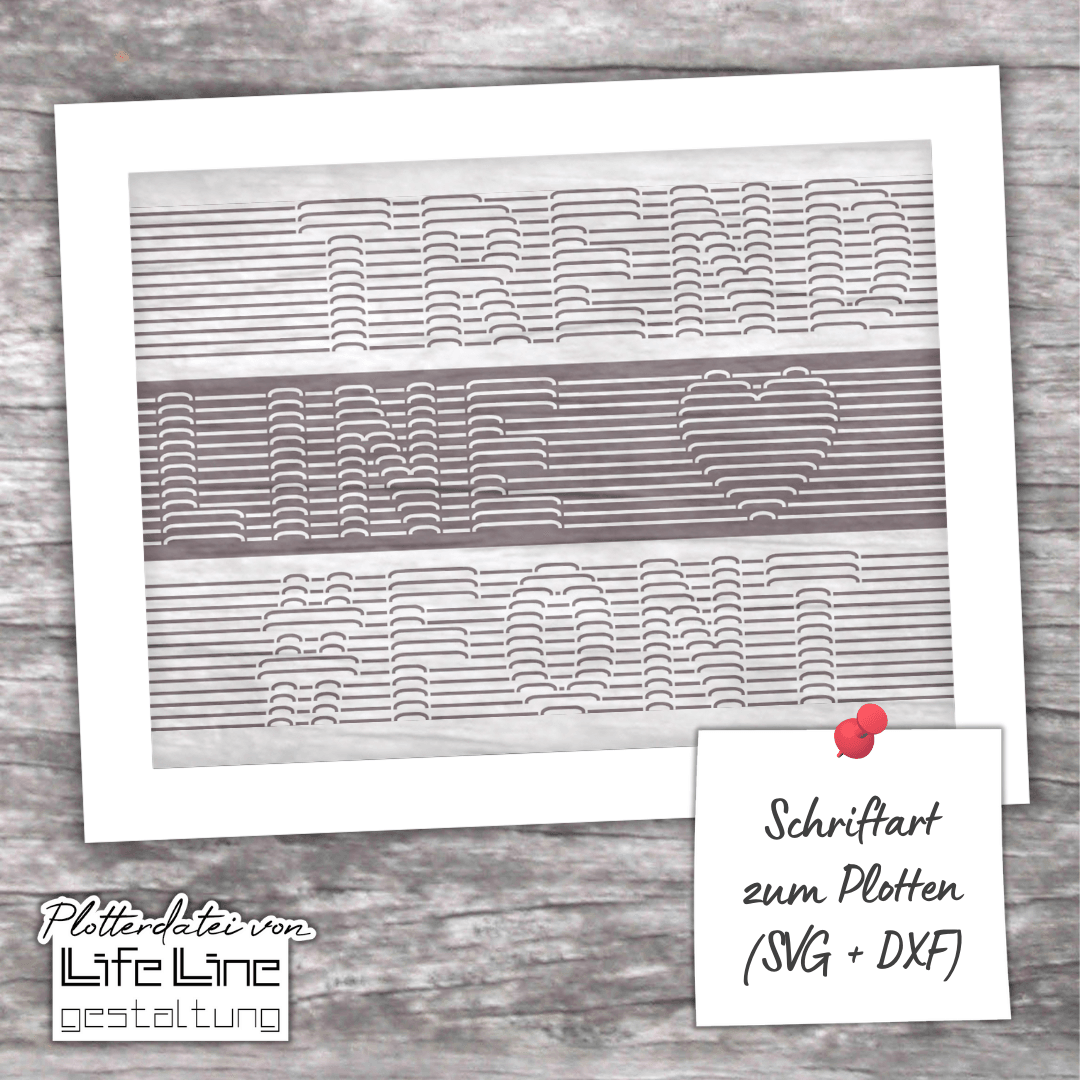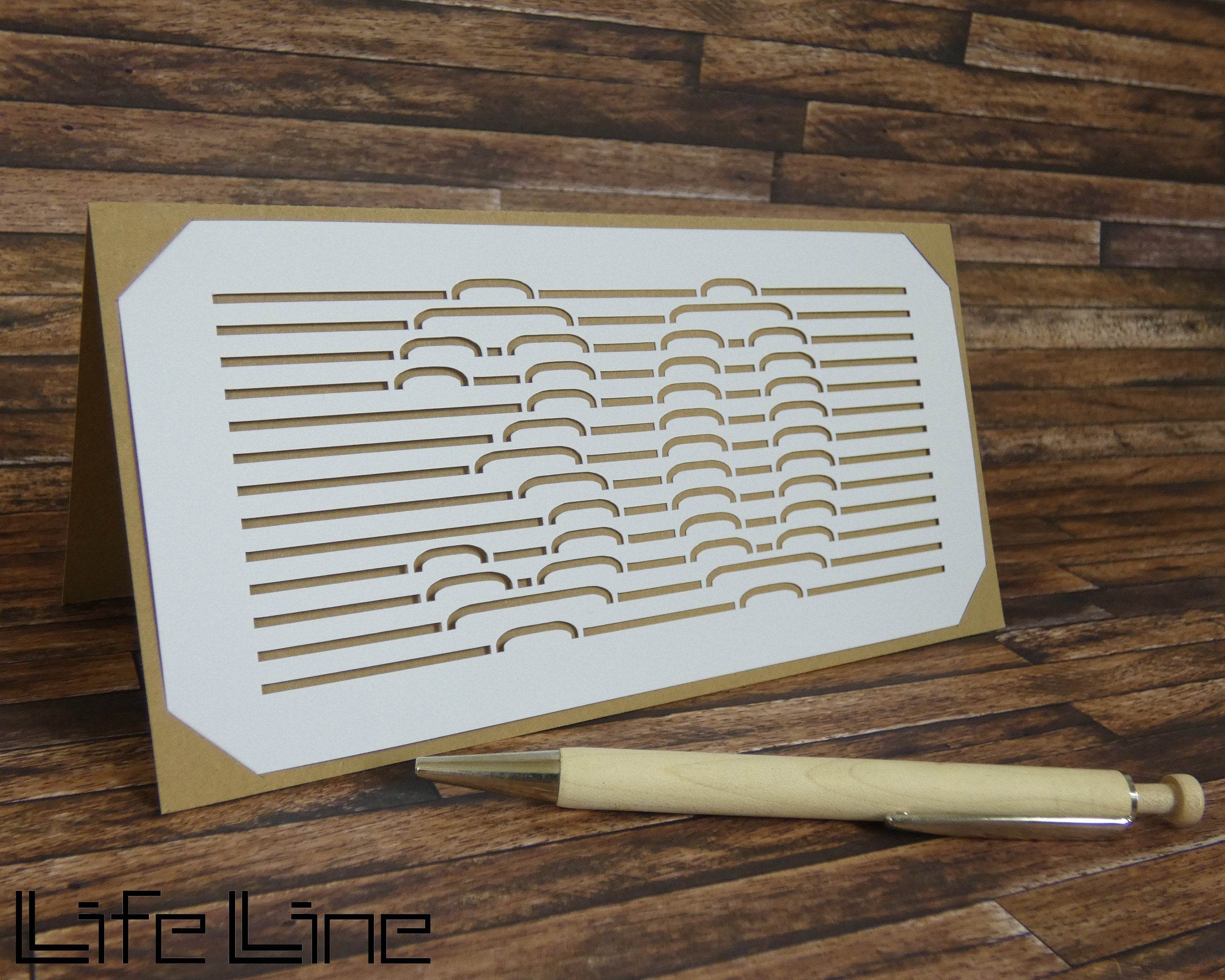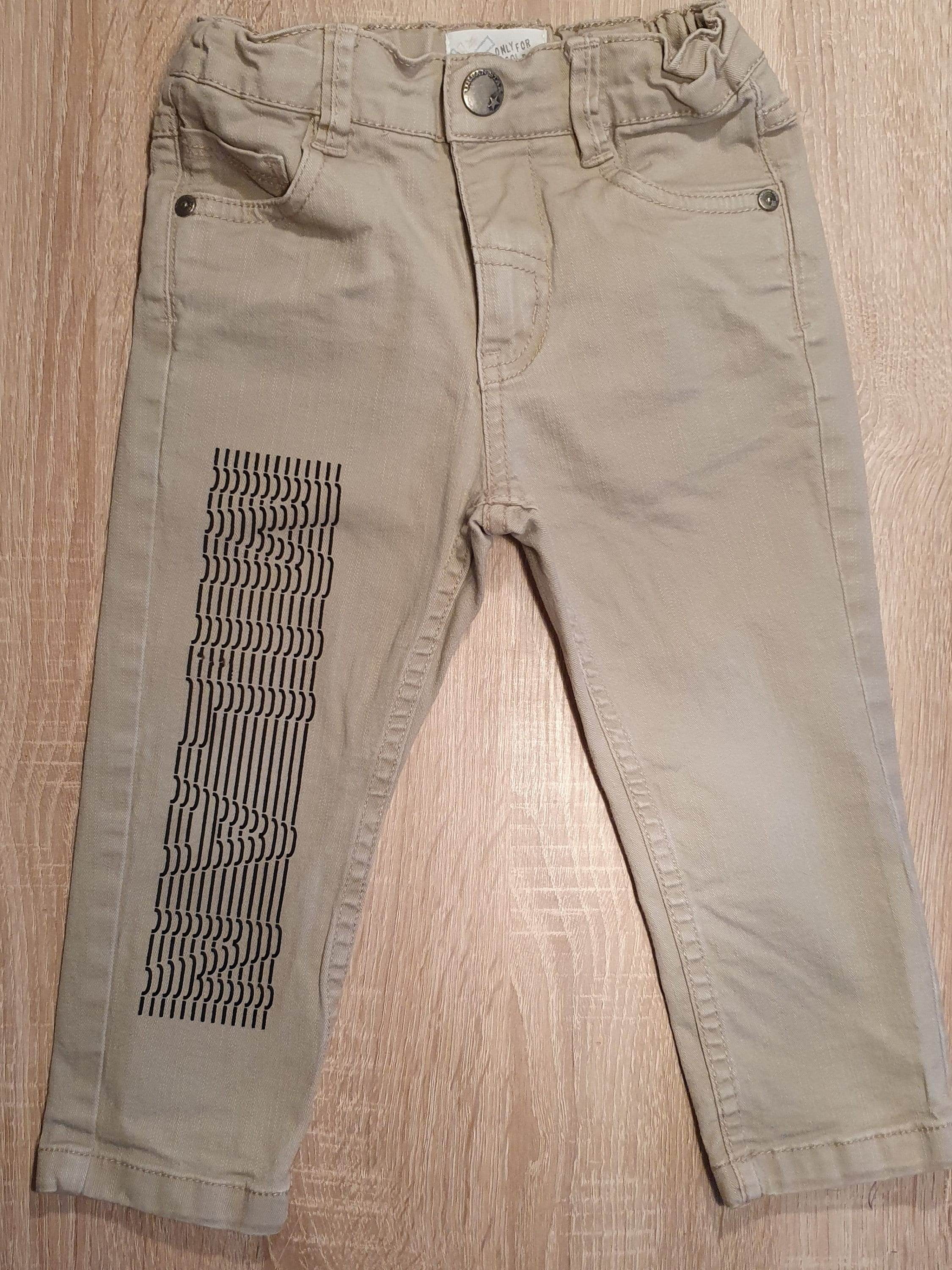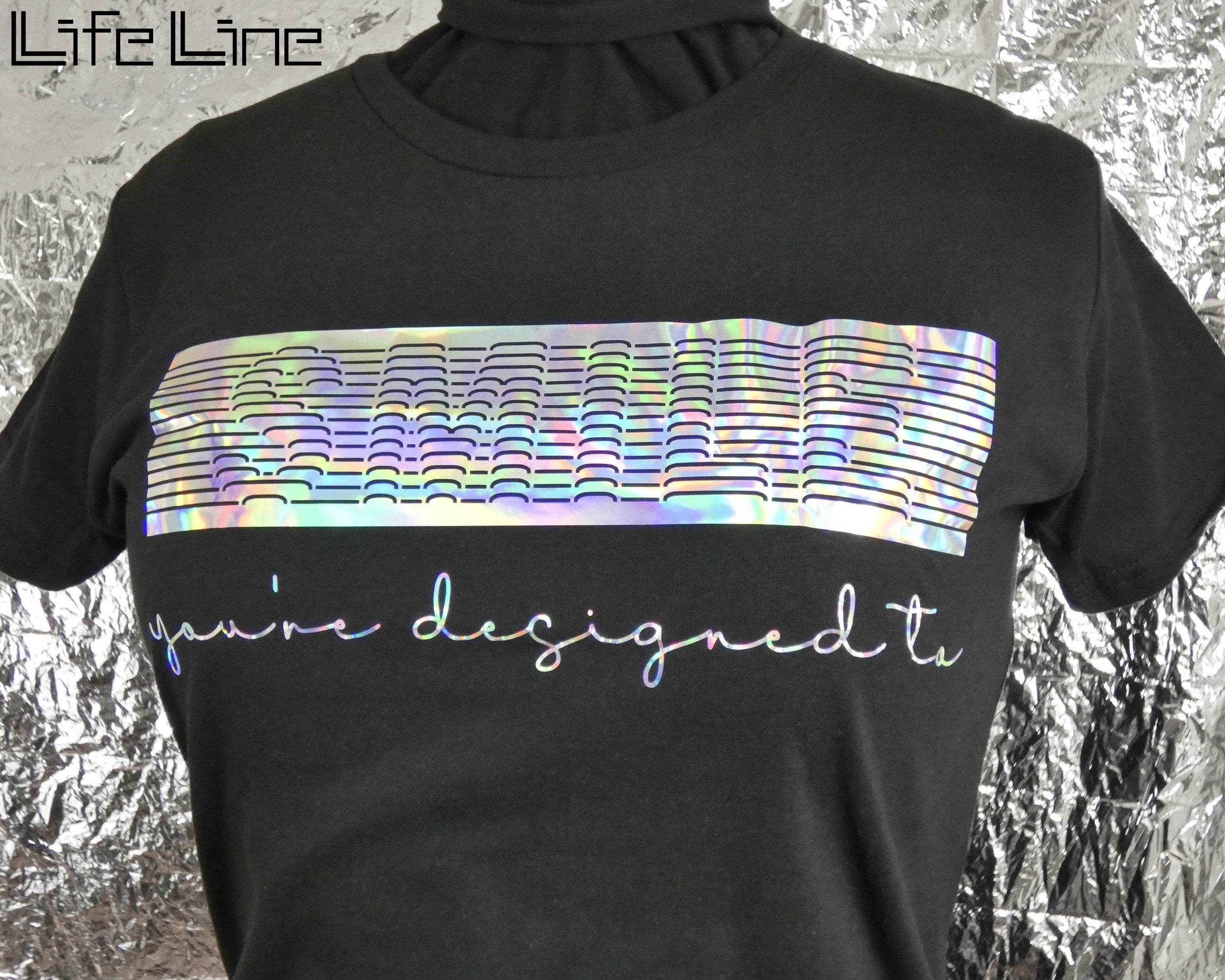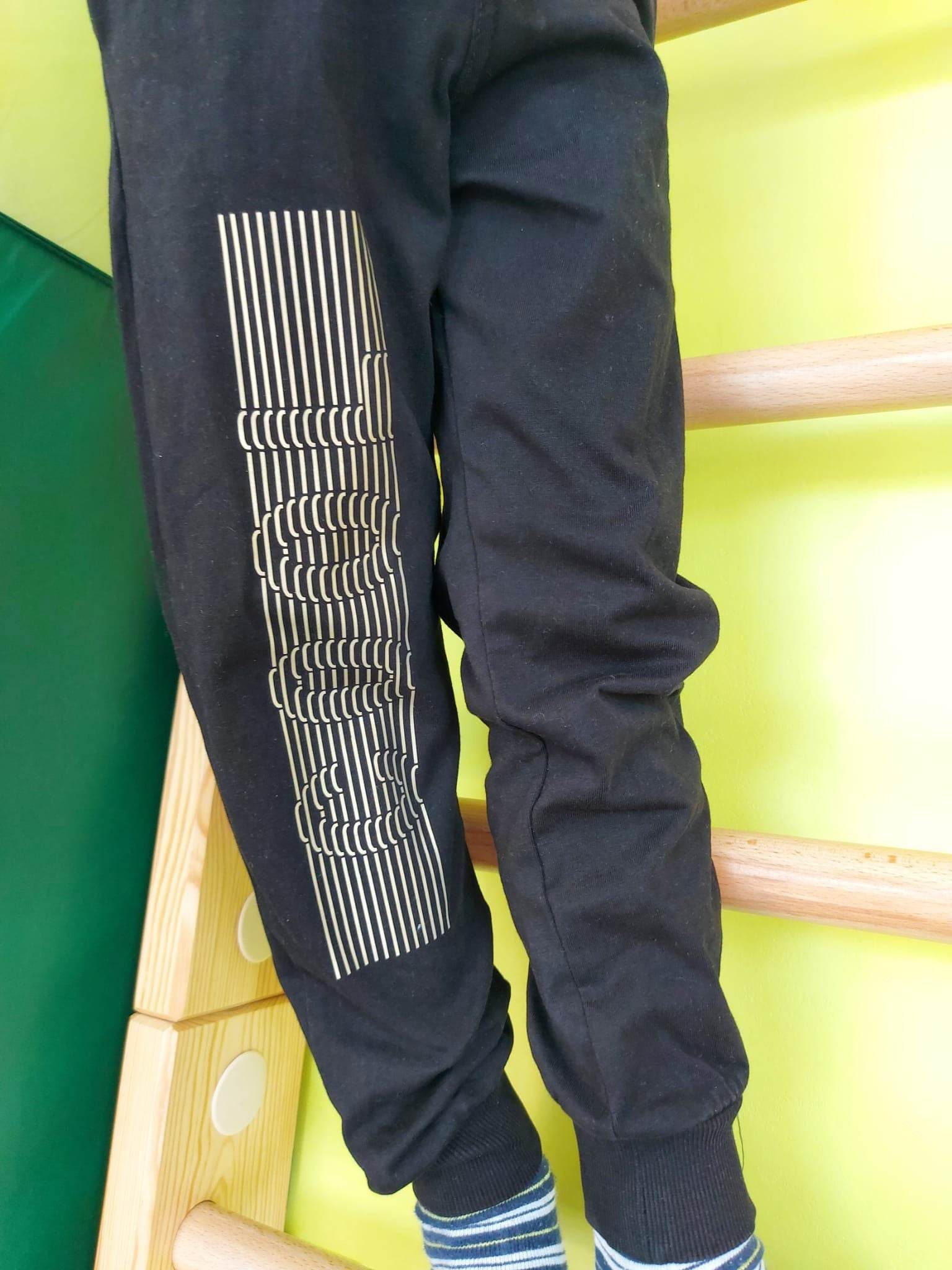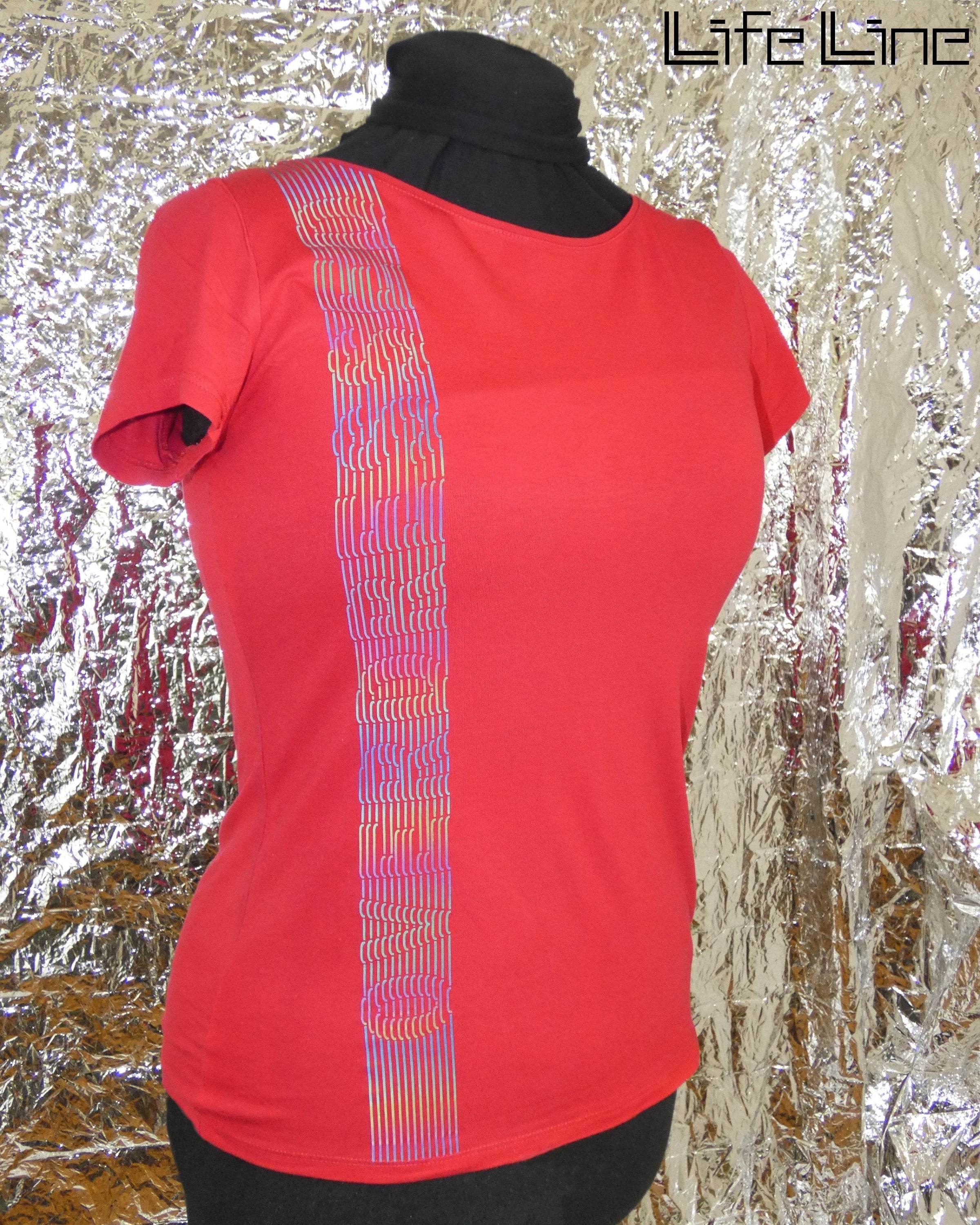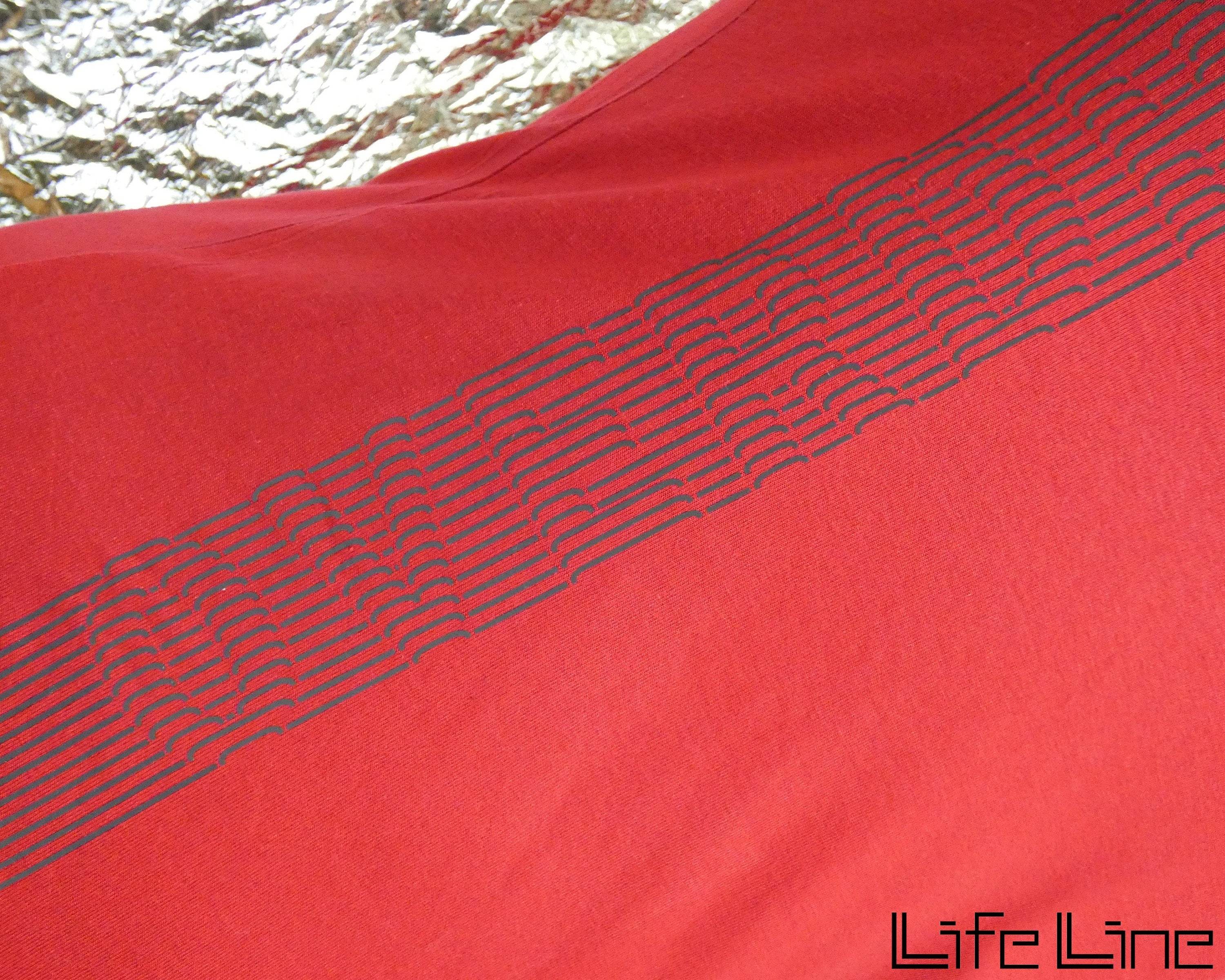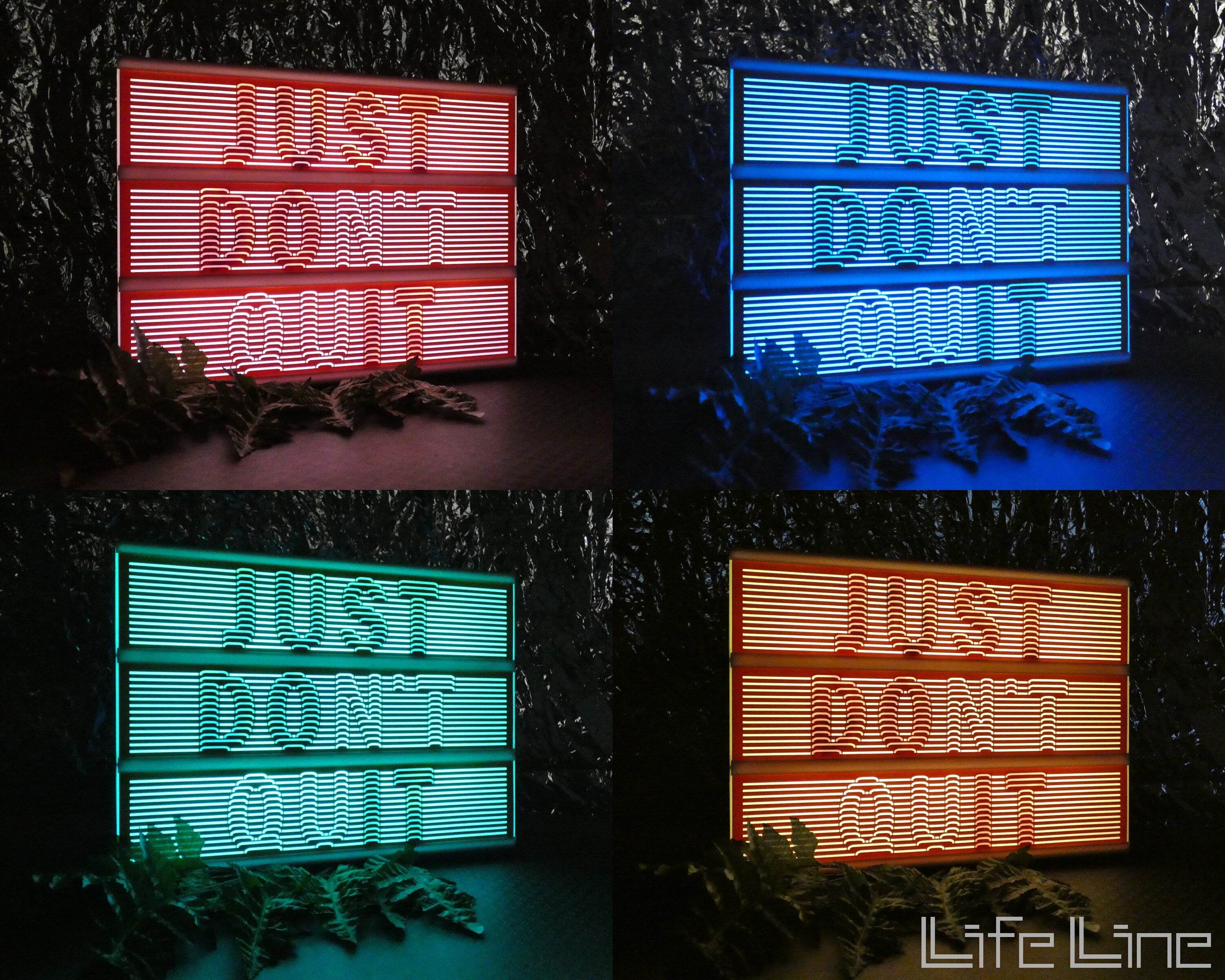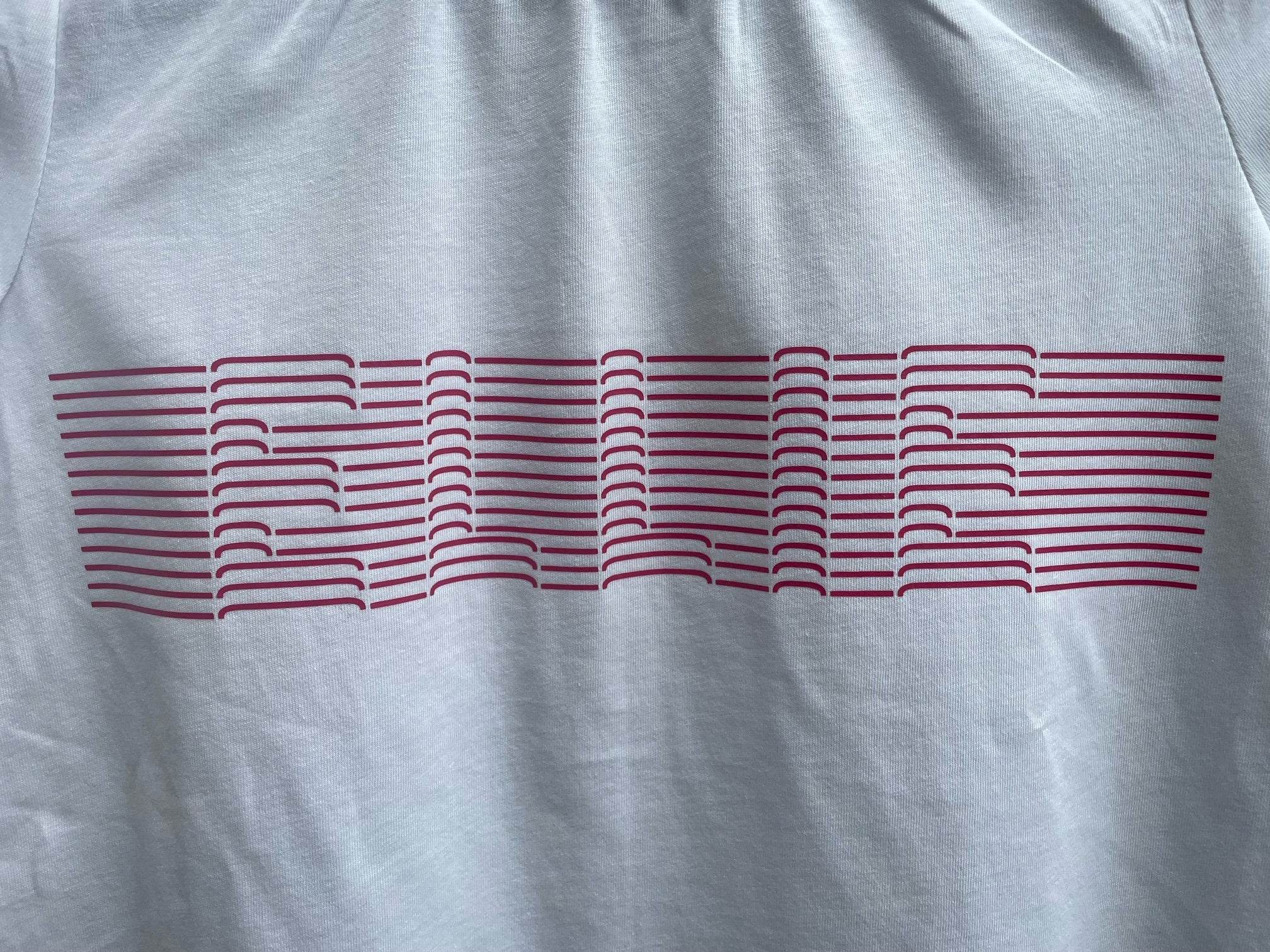
Schriftart TRENDLINE für Plotter svg + dxf
Schriftart mit 3D-Effekt zum Plotten von Statements etc., geeignet für Folie und Papier. Enthält 26 Buchstaben, 3 Umlaute, 10 Ziffern und 7 Sonderzeichen (&#♥?!-+).